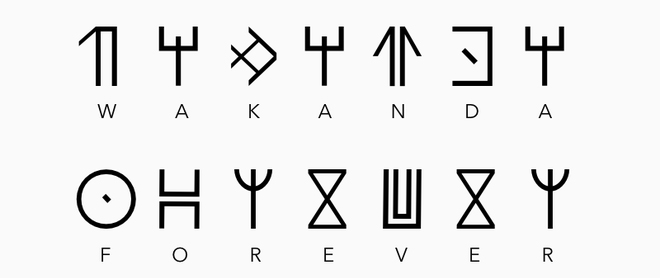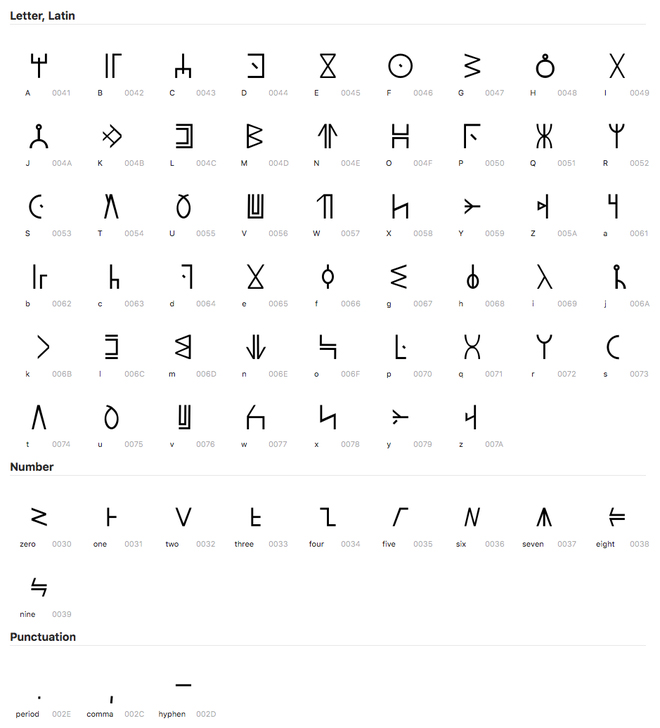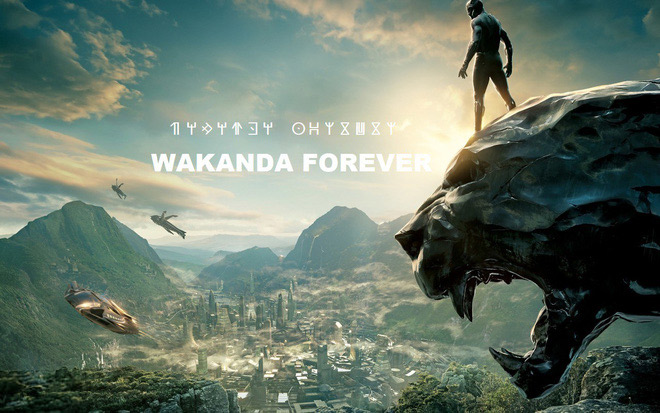
Tải ngay bộ font "Wakanda Forever" tuyệt đẹp được lấy cảm hứng từ ngôn ngữ trong bộ phim "Black Panther"
Giờ đây bạn có thể sử dụng ngôn ngữ Wakanda viễn tưởng, đầy tính tượng hình trong bộ phim bom tấn "Black Panther" để thỏa sức sáng tạo theo ý thích.
Lấy cảm hứng triệt để từ ngôn ngữ của quốc gia viễn tưởng Wakanda, quê hương của Black Panther, Adam Shady, một nhà thiết kế và cũng là thành viên của Dribbble (website hàng đầu của cộng đồng designer trên toàn thế giới) đã sáng tạo ra bộ font chữ "Wakanda Forever" và chia sẻ nó cho mọi người.
Font chữ Wakanda Forever
Font chữ Wakanda Forever.
Trên trang Dribbble cá nhân của mình, Adam chia sẻ: "Tôi rất thích bộ phim này và đã xem nó hai lần. Từ những hình ảnh về bảng chữ cái Wakanda trong bộ phim, tôi bắt đầu chuyển đổi nó thành bộ font chữ."
Ngoài ra, Adam cũng cho biết thêm đây là font chữ đầu tiên mà anh tạo ra, vì vậy sẽ có những sai sót về kí tự/khoảng cách giữa các kí tự. Những lỗi này sẽ được sửa chữa trong phiên bản cập nhật sắp tới.
Bảng chữ cái Wakanda với kí tự Latin
Bảng chữ cái Wakanda với kí tự Latin tương ứng.
Chữ của người Wakanda trong bộ phim được lấy cảm hứng từ chữ Nsibidi, có nguồn gốc từ sông Cross ở Đông Nam Nigeria. Hiện này, loại chữ viết này vẫn được sử dụng nhưng đang làm giảm đáng kể do công cuộc thực dân hóa và các tác động như giáo dục, tôn giáo...
Chữ Nsibidi, có nguồn gốc từ sông Cross ở Đông Nam Nigeria
Bộ font "Wakanda Forever" tuyệt đẹp dành cho người hâm mộ "Black Panther"Kết quả sau khi sử dụng với MS Paint.